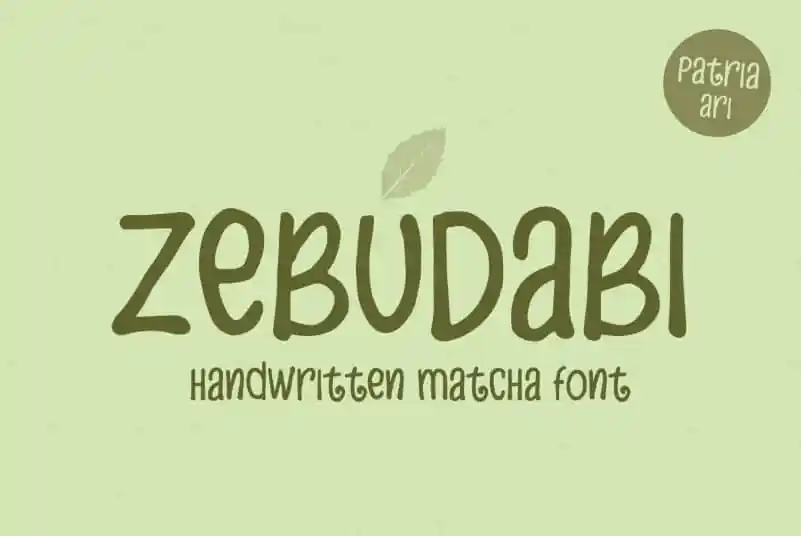
Introduzimos a Zebudabi Display Font, uma fonte cursiva feita à mão com formações únicas. Ideal para designers que buscam algo diferente e criativo, ela traz letras minúsculas e maiúsculas prontas para serem usadas de forma divertida, permitindo combinações únicas e inovadoras para projetos visuais. A Zebudabi é perfeitamente adaptável a uma variedade de aplicativos, desde capas de livros até sacolas de shopping ou materiais de merchandising, passando por posteres e títulos. Suas formas singelas e desenhadas à mão tornam a fonte perfeita para ilustrar citações ou criar um design único. Experimente Zebudabi na sua próxima criação e veja como ela pode dar vida ao seu trabalho!